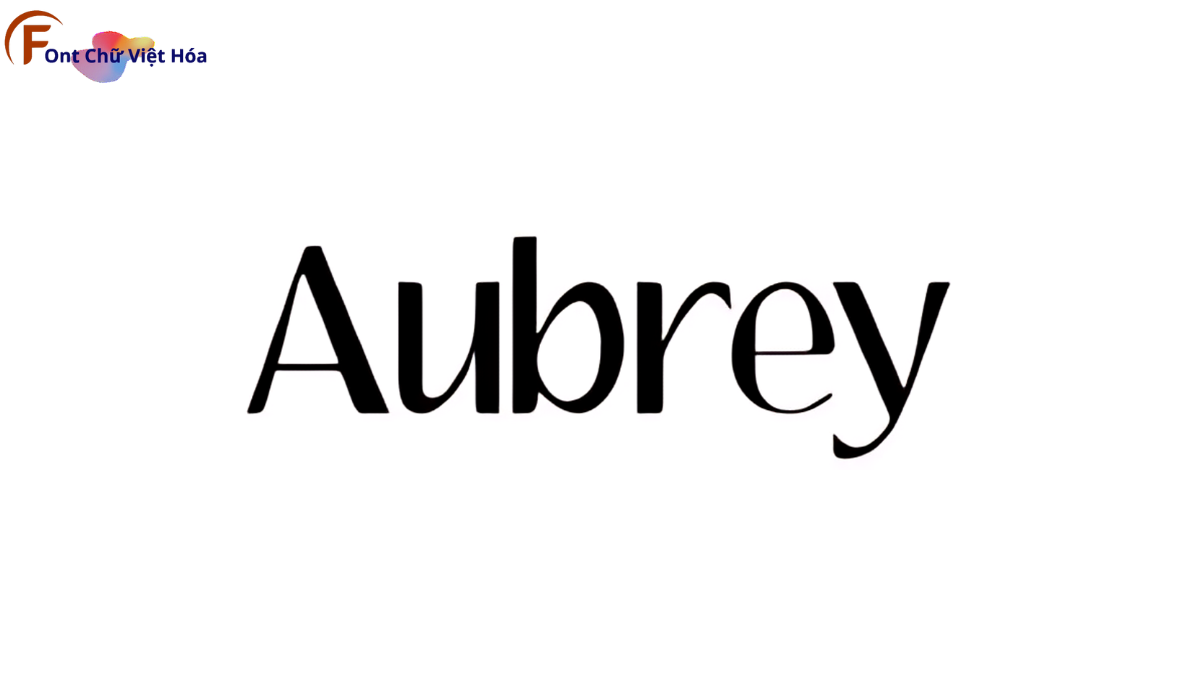
SFU Aubrey Font Việt Hóa
Phân loại: Cá tính
Kiểu chữ: Có chân
Độ dày: Regular, Bold
SFU Aubrey Font
Font SFU Aubrey Việt Hóa là một font chữ độc đáo, mang phong cách sans-serif hiện đại với các đường nét mạnh mẽ và cá tính, thuộc bộ font SFU. Thiết kế của SFU Aubrey tập trung vào sự rõ ràng và dễ đọc, đặc biệt phù hợp cho các thiết kế đòi hỏi tính thẩm mỹ cao như poster, logo, và tiêu đề. Với tỷ lệ chữ cân đối và các đường nét đậm, font này tạo ra ấn tượng thị giác mạnh mẽ và giúp tối ưu hóa không gian trong thiết kế. Font này cũng đã được Việt hóa, mang đến sự linh hoạt và tiện dụng cho các dự án thiết kế bằng tiếng Việt.